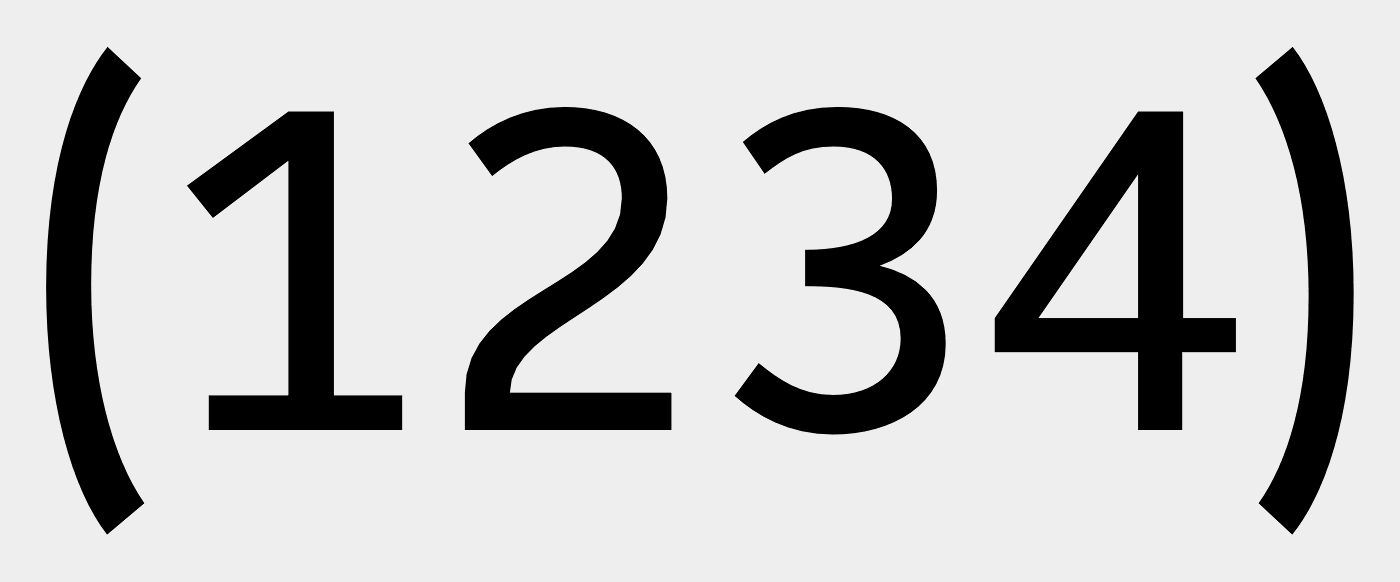
Nummern in »Pillenform«
ihr kennt das: mehrstellige nummern stehen – zumeist invers – auf farbigem hintergrund-feld. dieses feld ist oben und unten flach und links und rechts abgerundet. geht ganz leicht indem man eine textbox mit weißen zahlen auf eine pillenförmige fläche setzt.
noch eleganter und auch einfacher wird es, wenn man gleich einen entsprechenden font zur hand hat, der zahlen und hintergrund in einem liefert. viele dingbat-fonts bieten so etwas. allerdings nur für die ziffern 0 bis 9. wenn man mehrstellige zahlen auf diese art erzeugen will, braucht es einen font, der pro ziffer 3 varianten anbietet: 1. mit rundung links, 2. oben und unten und 3. rechts abgerundet. die fedra sans pro zum beispiel hat solche ziffern in der abteilung glyphenvarianten.
die frage ist jetzt nur: wie komme ich an die richtigen ziffern heran? über die glyphenpalette einzeln zusammenklicken kommt bei meinem projekt nicht in frage. viel zu mühsam bei hunderten von 3-stelligen zahlen. was mir vorschwebt, wäre ein open-type-gesteuerter automatismus, der je nach position die richtige variante auswählt. bei der fedra krieg ich das aber leider nicht hin.
gibt es überhaupt einen font der das kann? wenn ja welchen?
(Leider kann die Vorschau die per Opentype erzeugte Form nicht zeigen, aber das sollte genau das sein, was du suchst.)
EDIT: Oder geht das hier nur bis zu drei Stellen?
EDIT₂: Zumindest bekomme ich das auf myfonts.com nicht hin. Aber selbst wenn es nicht allein über Ligaturen bzw. kontextbasierte Ersetzungen funktionieren sollte, ließe sich das doch sicher über ein Update nachrüsten, das erlaubt, die negativen bzw. eingekästelten Mittelziffern per stylistic set zu erzwingen. Wie wärs, FDI? :biglove:
Was klappt denn nicht?
ich kann die gewünschten ziffern (der fedra sans pro) nicht via opentype aktivieren. erreiche sie nur über die glyphenpalette. was zur folge hat, dass ich alle neu eingeben müsste, was mühsam und fehleranfällig ist.
hier die lösung (steht eh im beschreibungs-pdf, lesen muss man’s halt auch :nicken: ):
vorher und nachher eine klammer eingeben und dann via open type »bedingte ligaturen« einschalten.